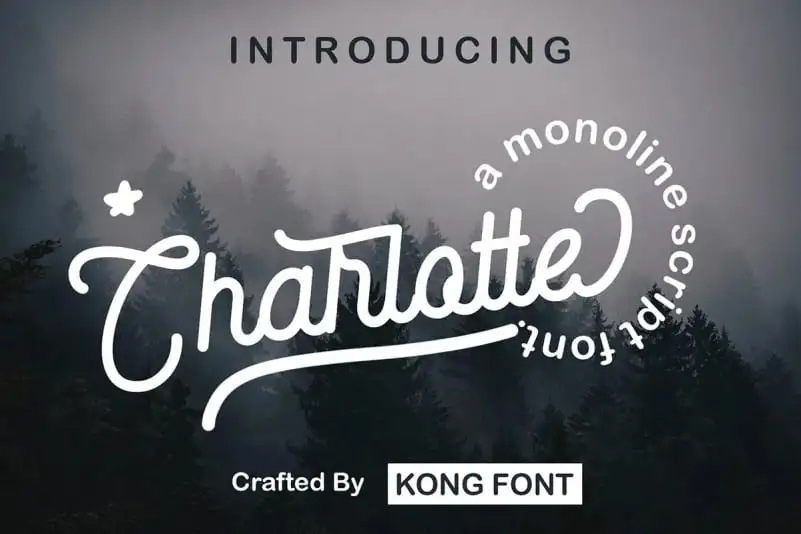
Charlotte Handwritten Font – Download Grátis
A Charlotte Handwritten Font é uma escolha perfeita para designers que procuram adicionar um toque elegante e moderno a seus projetos. Fabricada pela fontkong, essa fonte script apresenta uma aparência única e sofisticada, parecendo como uma assinatura autêntica. O designer intencionalmente criou o formato com ligaturas únicas e alternadas, oferecendo um recurso inovador que pode ser facilmente integrado em qualquer projeto de design. Seja para contratos legais ou editoriais, essa fonte se destaca como uma opção criativa que não apenas complementa seu estilo visual, mas também adiciona profundidade e personalização ao texto. Ideal tanto para criar design editorial, como para artes gráficas digitais, a Charlotte Handwritten Font é um recurso indispensável para qualquer designer buscando destacar suas criações.